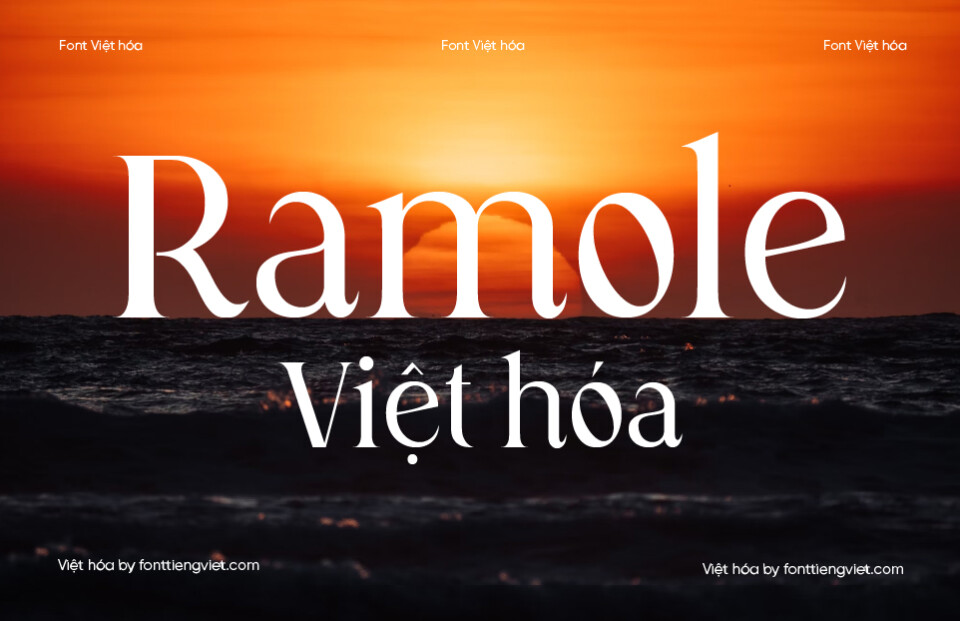
Font Việt hóa 1FTV VIP Ramole
Tải Bộ Font Việt hóa 1FTV VIP Ramole Sang Trọng Và Tinh Tế Cho Thiết Kế
Trong thế giới đồ họa hiện đại, việc lựa chọn một bộ Font Việt hóa 1FTV VIP Ramole chất lượng là yếu tố then chốt để tạo nên sự khác biệt cho tác phẩm. Đối với các bạn học sinh và giáo viên, một mẫu Font Miễn Phí đẹp không chỉ giúp bài thuyết trình trở nên sinh động mà còn thể hiện được gu thẩm mỹ chuyên nghiệp. Ramole được biết đến là một phông chữ mang phong cách Serif tân cổ điển, vừa giữ được nét thanh lịch truyền thống, vừa toát lên vẻ hào nhoáng của thời đại mới. Phiên bản Việt hóa bởi 1FTV đã tối ưu hóa toàn bộ các dấu câu tiếng Việt, giúp người dùng sử dụng mượt mà trên mọi phần mềm thiết kế từ đơn giản đến chuyên sâu.
Đặc điểm nổi bật của bộ Font Việt hóa 1FTV VIP Ramole
Bộ font này gây ấn tượng mạnh mẽ nhờ sự kết hợp hài hòa giữa những nét thanh và nét đậm tinh tế. Đây là lựa chọn lý tưởng cho những ai đang tìm kiếm sự sang trọng nhưng không quá cầu kỳ. Cấu trúc chữ của Ramole có độ mở lớn, tạo cảm giác thoáng đãng và dễ đọc ngay cả khi hiển thị ở kích thước nhỏ trên tài liệu học tập.
Tính ứng dụng cao trong học đường và đời sống
Với Font Việt hóa 1FTV VIP Ramole, các bạn có thể thỏa sức sáng tạo trên nhiều nền tảng khác nhau. Đối với học sinh, bộ font này cực kỳ phù hợp để làm bìa báo tường, thiết kế thiệp chúc mừng thầy cô hoặc làm tiêu đề cho các dự án nghiên cứu khoa học. Sự chỉn chu trong từng nét chữ giúp nội dung truyền tải trở nên uy tín và chuyên nghiệp hơn. Trong khi đó, các thầy cô giáo có thể sử dụng font chữ này để thiết kế bài giảng điện tử, giúp học sinh dễ dàng theo dõi và ghi nhớ kiến thức một cách hứng thú.
Khả năng tương thích và tối ưu hóa tiếng Việt
Điểm cộng lớn nhất của phiên bản này chính là việc xử lý các dấu tiếng Việt cực kỳ khéo léo. Thông thường, các font ngoại nhập khi gõ tiếng Việt hay bị lỗi nhảy chữ hoặc dấu bị đè lên nét chính. Tuy nhiên, với 1FTV VIP Ramole, mọi ký tự như ă, â, đ, hay các dấu thanh đều được tinh chỉnh khoảng cách tỉ mỉ, đảm bảo tính thẩm mỹ cao nhất cho văn bản. Bạn có thể dễ dàng cài đặt font trên Windows, macOS và sử dụng trong các ứng dụng phổ biến như Word, PowerPoint hay Canva.
Cách sử dụng Font Việt hóa 1FTV VIP Ramole hiệu quả
Để tận dụng tối đa vẻ đẹp của bộ chữ này, bạn nên ưu tiên sử dụng nó cho các tiêu đề lớn hoặc các đoạn trích dẫn ngắn. Khi kết hợp Ramole với một font Sans-serif đơn giản cho phần nội dung chính, bạn sẽ tạo ra một hệ thống phân cấp thị giác hoàn hảo. Đừng quên điều chỉnh khoảng cách dòng (leading) rộng hơn một chút để các nét chân chữ Serif có không gian tỏa sáng, tránh gây cảm giác rối mắt cho người xem.
Kết luận về bộ sưu tập font chữ cao cấp
Việc sở hữu bộ Font Việt hóa 1FTV VIP Ramole trong máy tính sẽ giúp kho tài nguyên sáng tạo của bạn trở nên phong phú và đẳng cấp hơn. Đây không chỉ đơn thuần là một công cụ trình bày mà còn là nguồn cảm hứng để chúng ta hoàn thiện các ý tưởng độc đáo. Hãy truy cập ngay kho dữ liệu Font Miễn Phí, Font Việt Hóa, Font Việt hóa 1FTV VIP Ramole để tải về và trải nghiệm sự khác biệt. Hy vọng rằng với chia sẻ này, các bạn sẽ có thêm nhiều tác phẩm thiết kế ấn tượng và đạt kết quả cao trong học tập cũng như công việc hằng ngày.